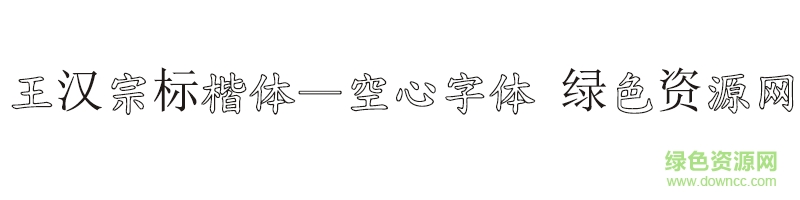
王汉宗标楷体—空心
王汉宗标楷体—空心字体是一款比较具有特色的汉子字体,空心字体给人非常具有立体感,深受广大书法家和年轻人的喜爱,还有更多好看字体尽情期待,欢迎到绿色资源网下载体验!
王汉宗标楷体—空心字体介绍
王汉宗标楷体—空心是王汉宗类标楷字体,字体效果比较正规,喜欢标楷体字的朋友可以下载使用看看效果如何。
王汉宗标楷体—空心字体